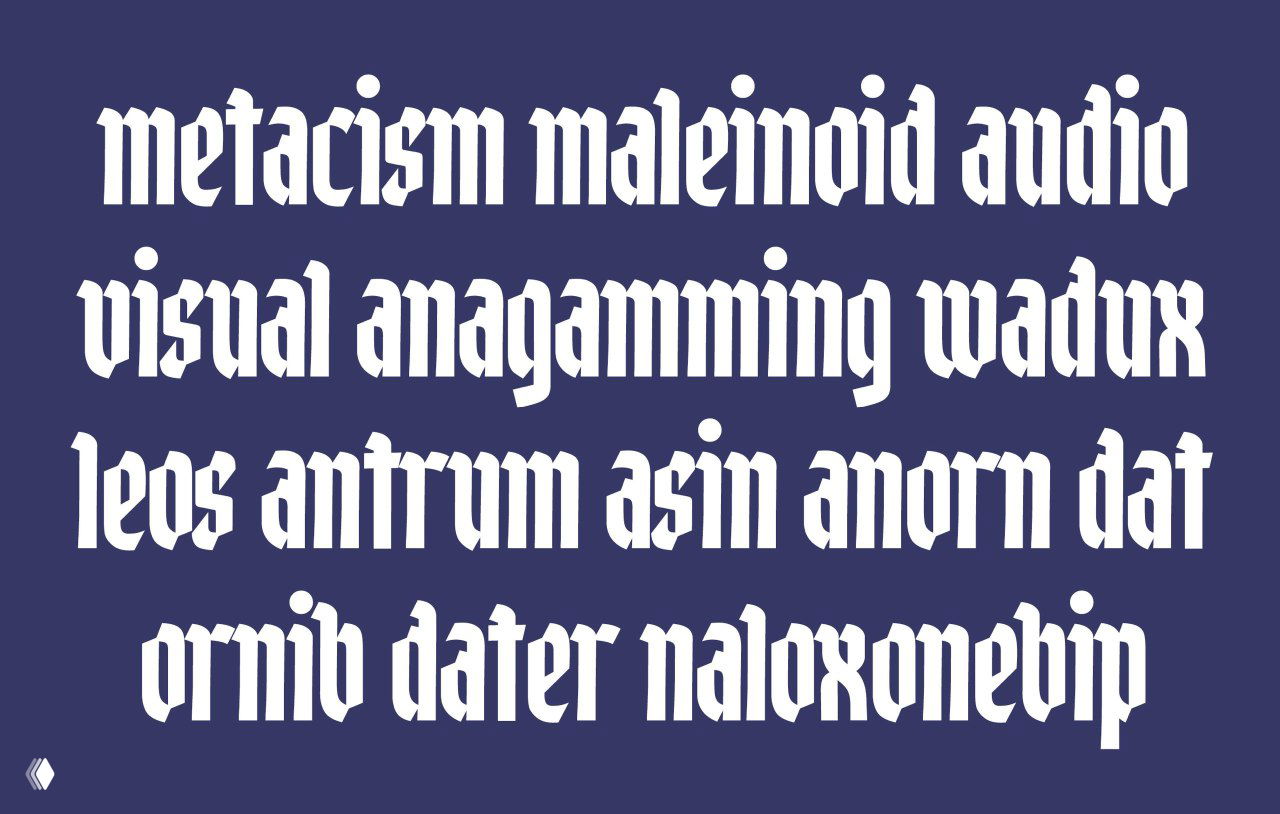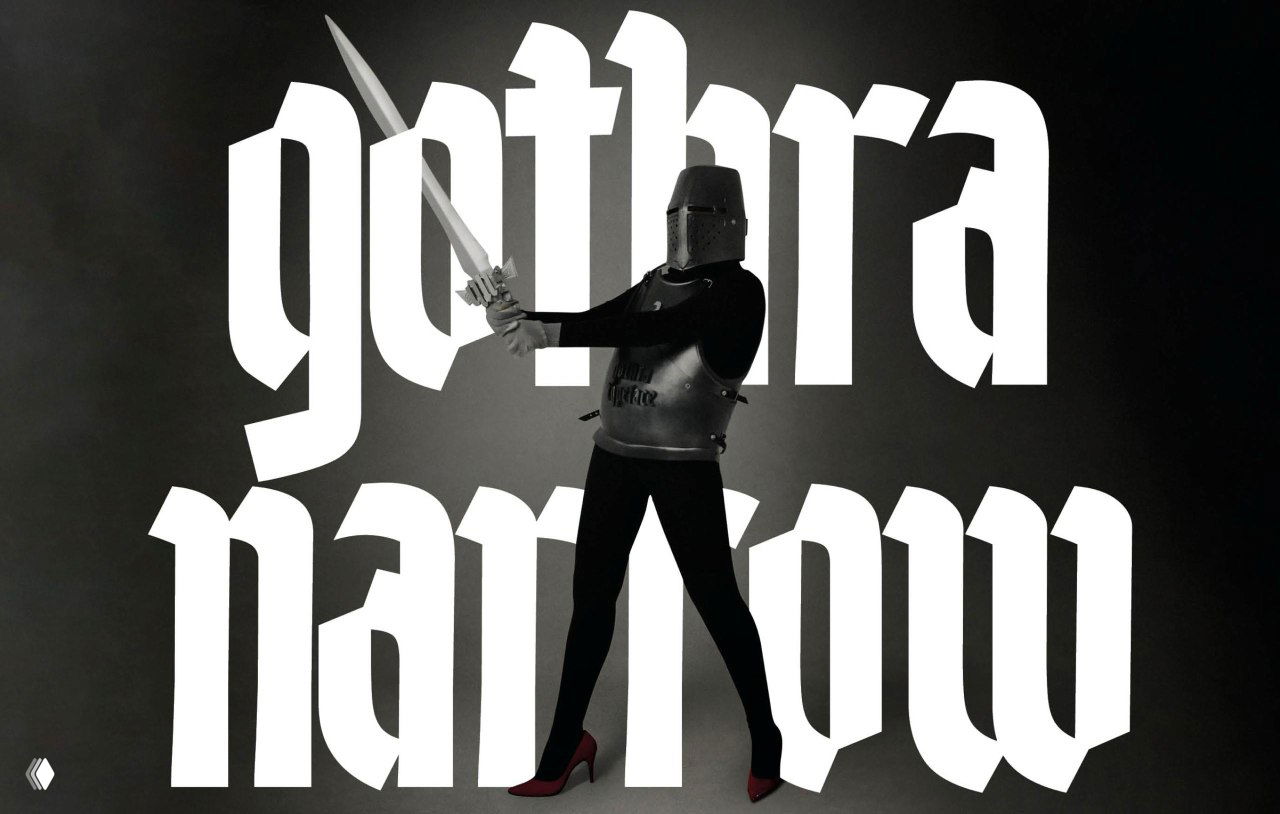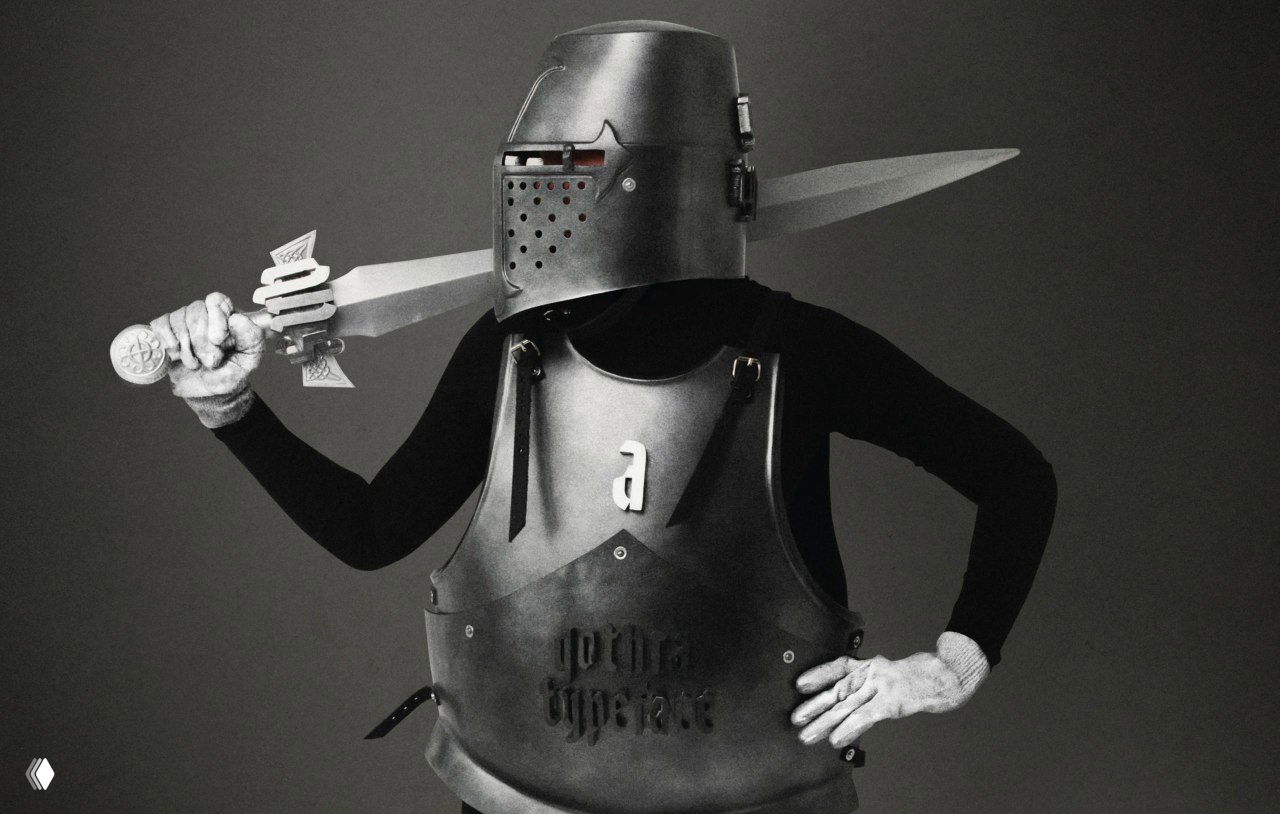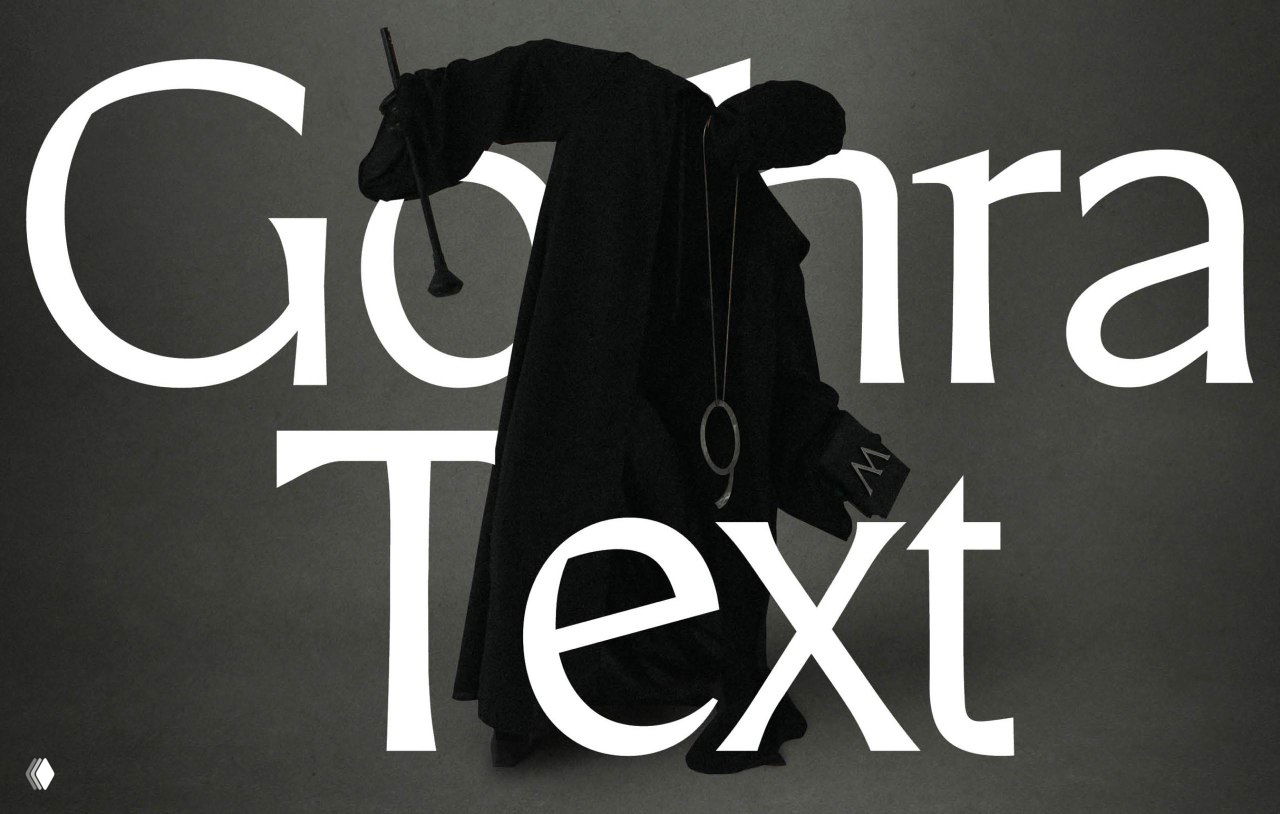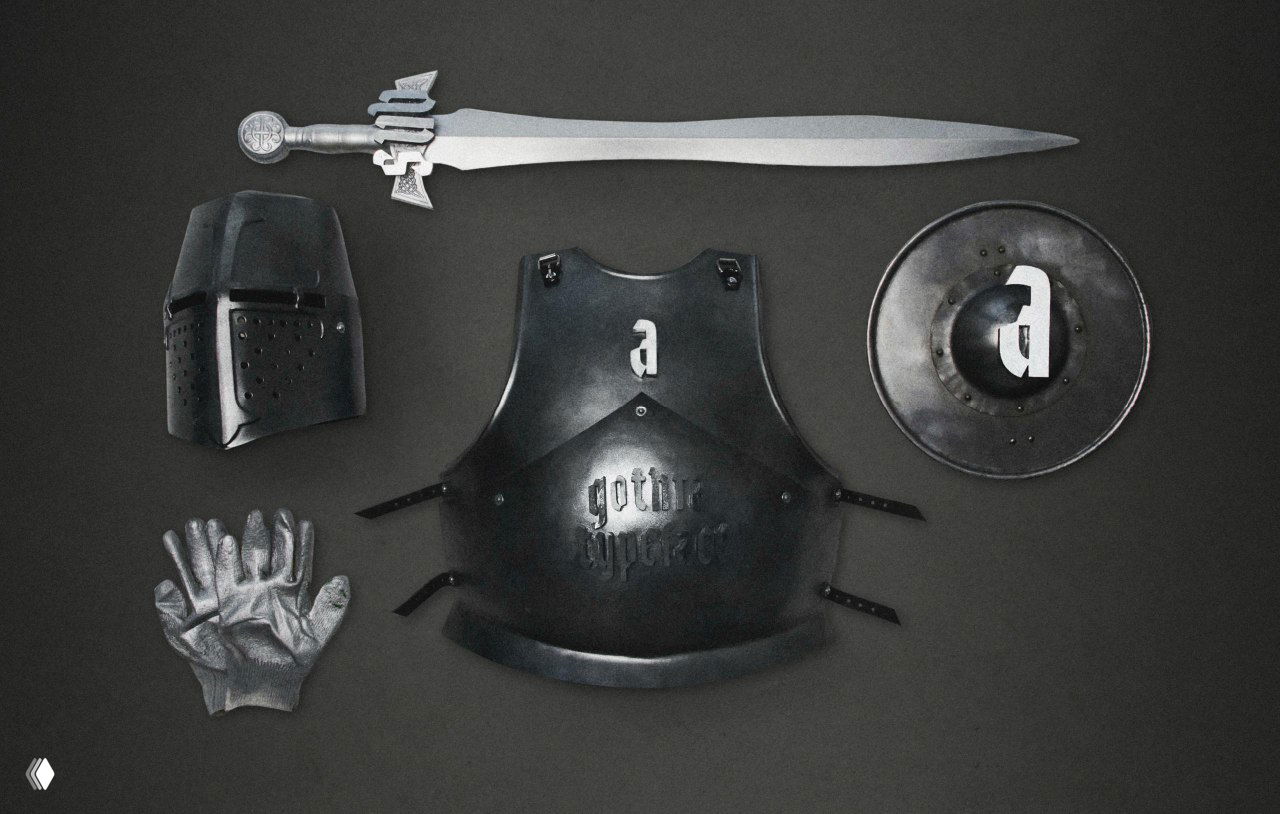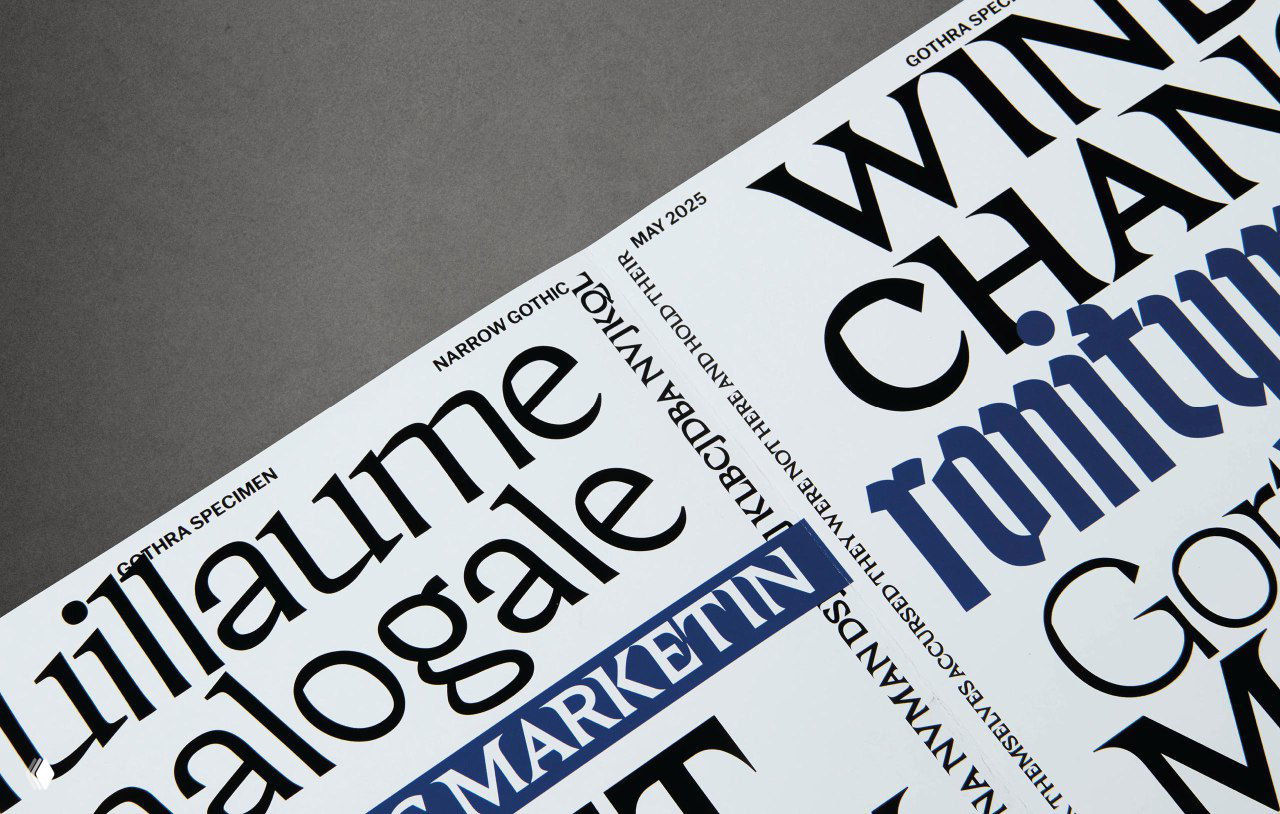
Вариативный шрифт GOTHRA
GOTHRAвариативный шрифтготический почерк
на основе готического почерка. Курсовой проект студентки ВШЭ Полины Гайнуллиной.
GOTHRA — шрифтовая семья, разработанная на основе готического почерка. Гарнитура состоит из трёх начертаний, два из которых вариативные — ось жирности и ось наклона — и одно статическое — узкое. Шрифт подходит для заголовков и крупного набора, айдентики и плакатов, и прочих проектов, в дизайне которых нужен акцентный, но типографичный шрифт, хранящий в себе память пера.
Постер-спецификация шрифта GOTHRA: крупные белые дисплейные буквы на тёмном фоне с тканевым реквизитом и контрастной подачей.
Спецификация GOTHRA
Силуэт в чёрной одежде с крупным медальоном на цепи и блокнотом с литерой — стилизованная художественная сцена для презентации шрифта.
Стилизованный портрет с медальоном
Строка набора GOTHRA: белые готические формы на насыщенном синем фоне, демонстрация вариативных начертаний и плотности набора.
Образцы набора на синем фоне
Рекламный кадр: фигура в рыцарской позе на фоне крупного дисплейного надписи GOTHRA — чёрно‑белая стилизация для постера шрифта.
Рекламный кадр с рыцарём
Портрет в рыцарских доспехах с мечом и нагрудником, оформленный в эстетике презентации гарнитуры и фирменных образов проекта GOTHRA.
Рыцарь в доспехах для брендинга
Логотип «Gothra display» на синим фоне в компактном формате, демонстрация варианта брендинга и фирменного знака шрифта.
Компактная версия логотипа
Крупный силуэт фигуры на фоне типографического заголовка «Gothra Text», игра масштаба между фотографией и набором букв.
Игры масштаба с заголовком
Набор реквизита: шлем, панцирь, щит с литерой и перчатка, выложенные на тёмном фоне как атрибуты визуальной концепции шрифта.
Реквизит и элементы доспехов
Макрофотография тиснёного металлического блока с рельефными буквами, детальное изображение текстур литер и обработки материала.
Тиснение и текстуры литер
Разворот спецификации GOTHRA: страница с образцами гарнитуры, вариантами начертаний и типографскими сетками для демонстрации использования.
Разворот спецификации шрифта